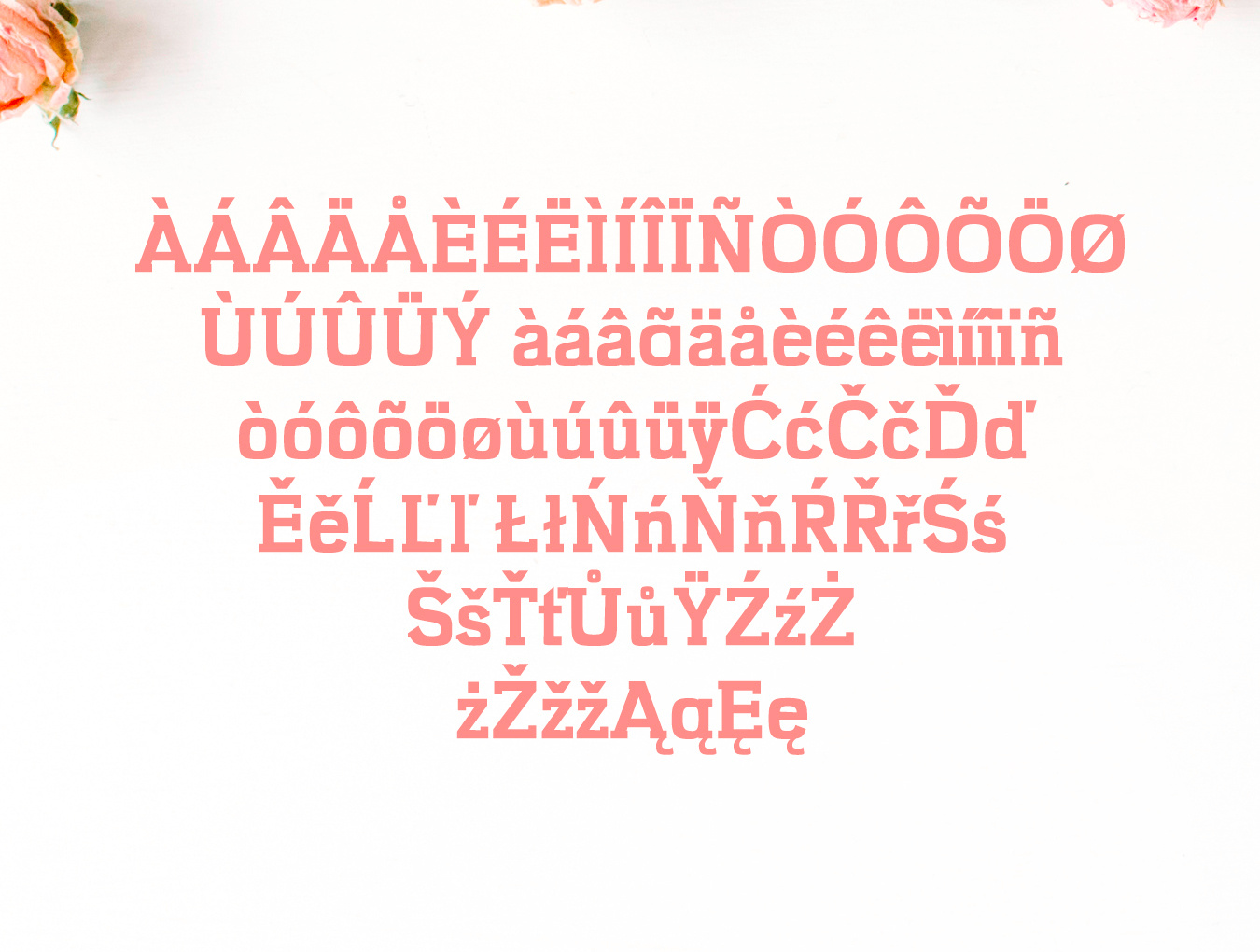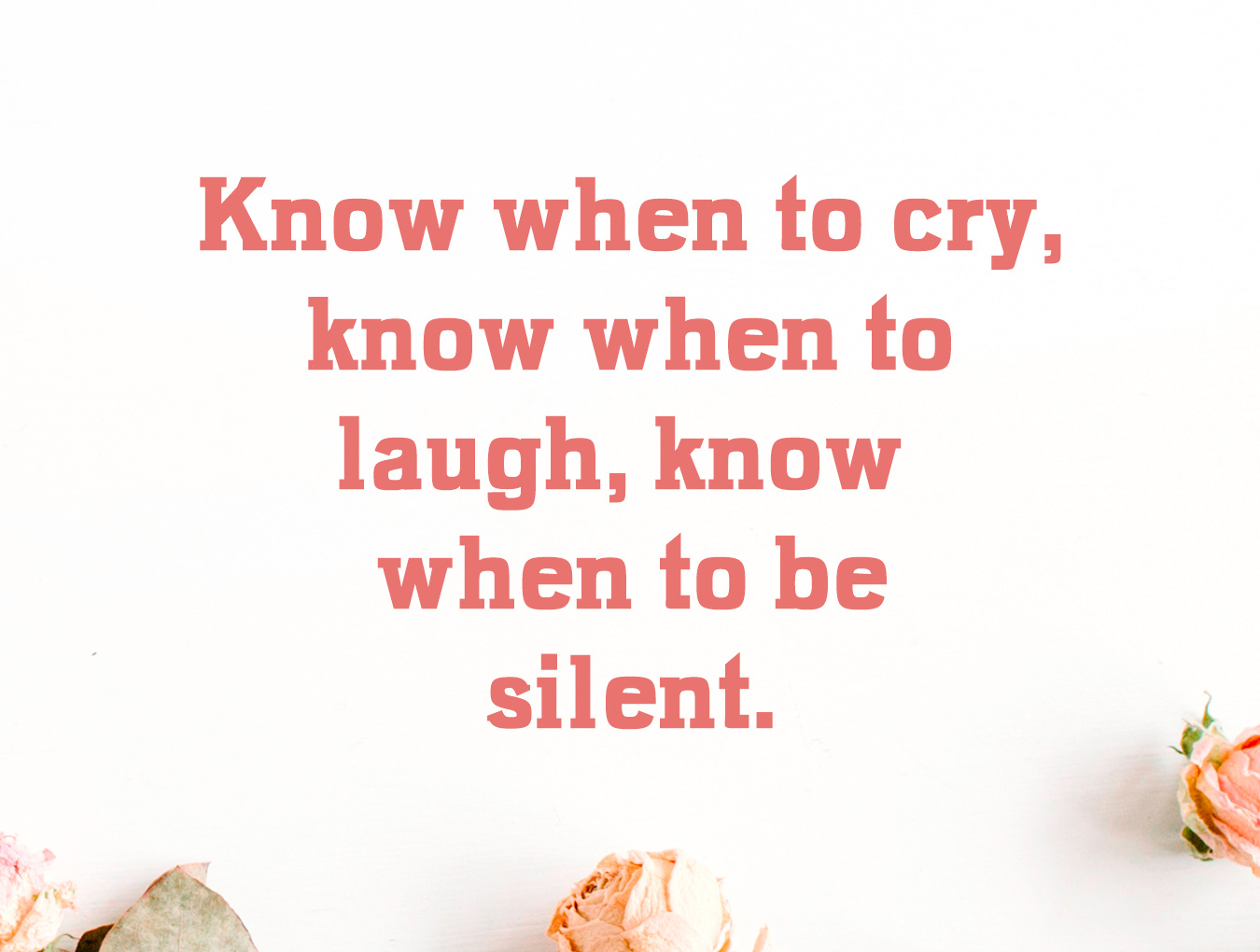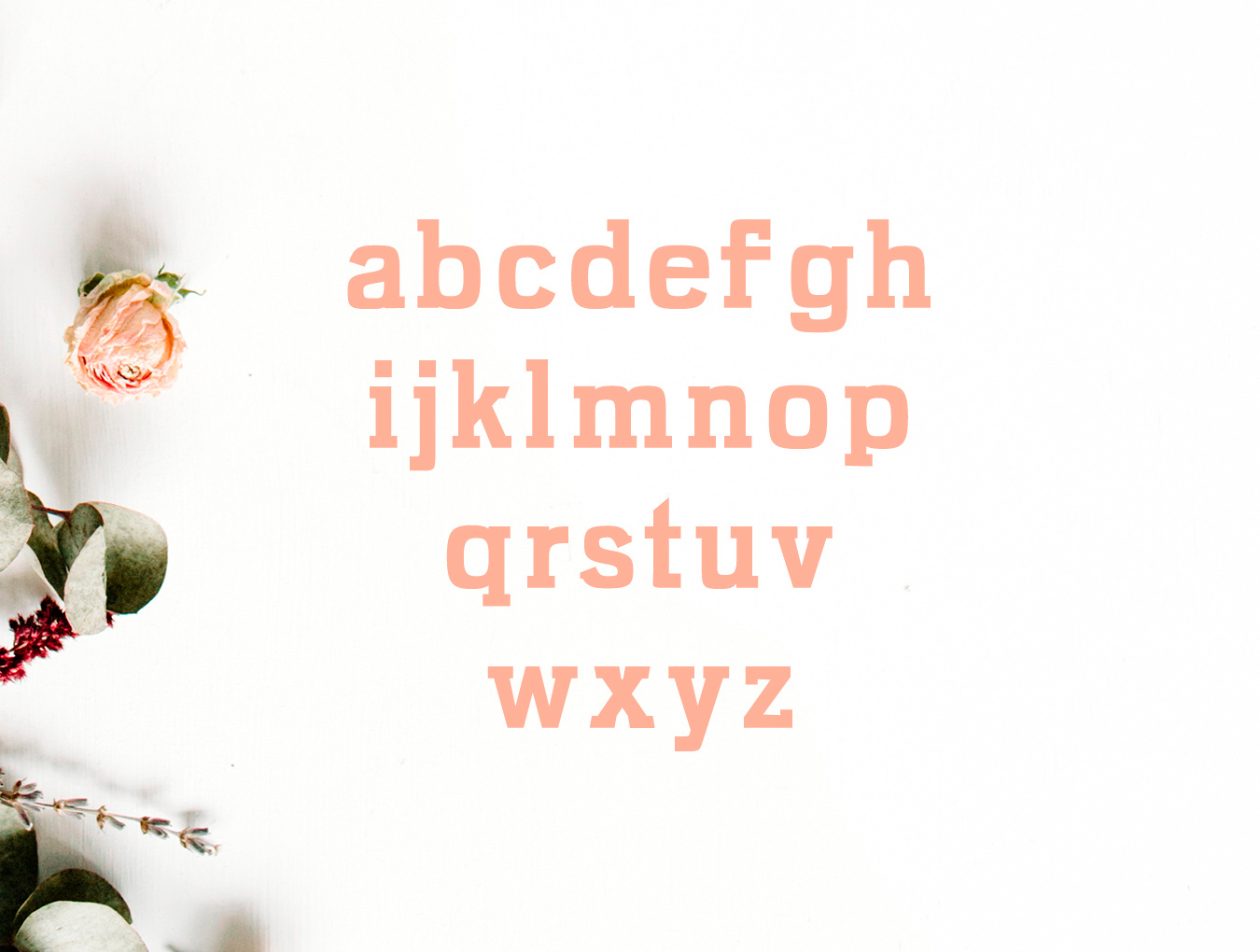
Kaayla Slab Serif 4字体家庭装,Kaayla Slab Serif
Kaayla Slab Serif字体套装包含4个重量,适合制作创意展示。它是我们商店中可爱而独特的平板衬线字体,让您可以让每个单词看起来都非常时尚!它最适合现代/干净的设计,标识,标题,横幅和模板等。如果你想尝试一个优雅的外观,它看起来华丽的所有大写间距,或美丽的大写和小写字母为完全永恒的东西。